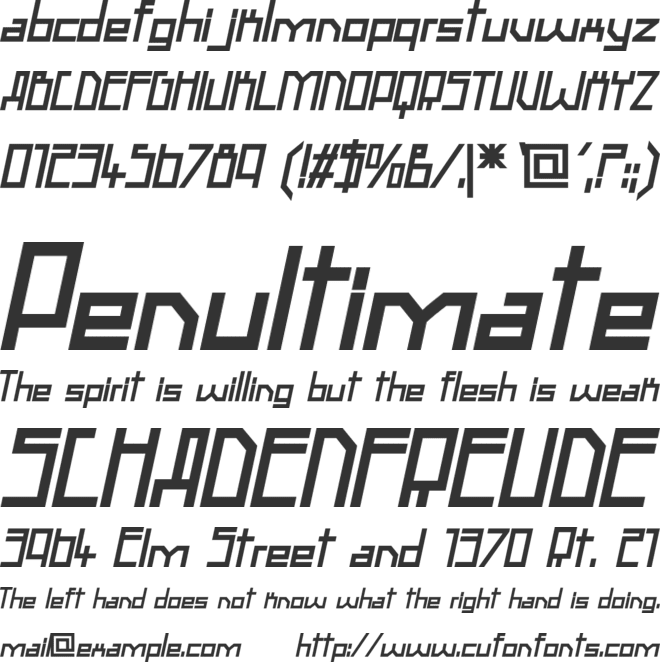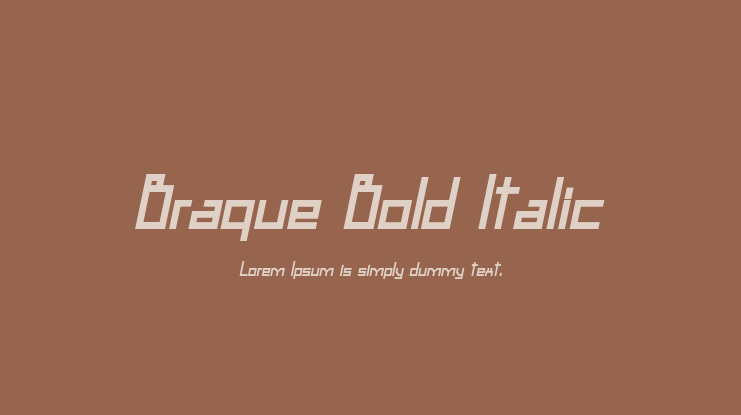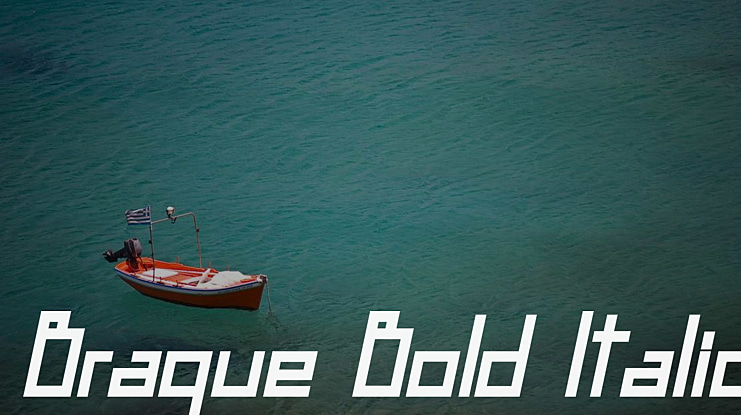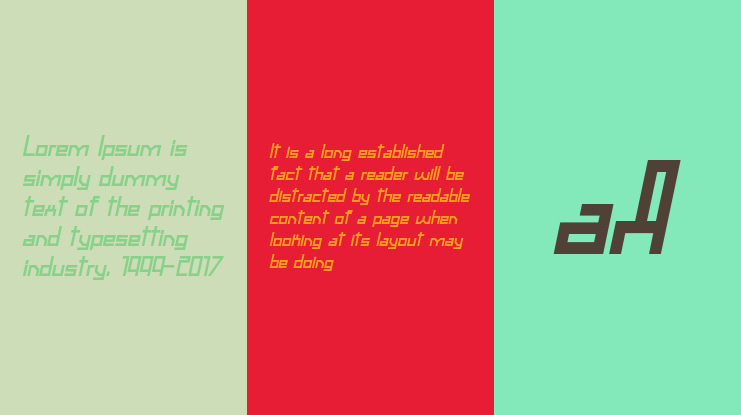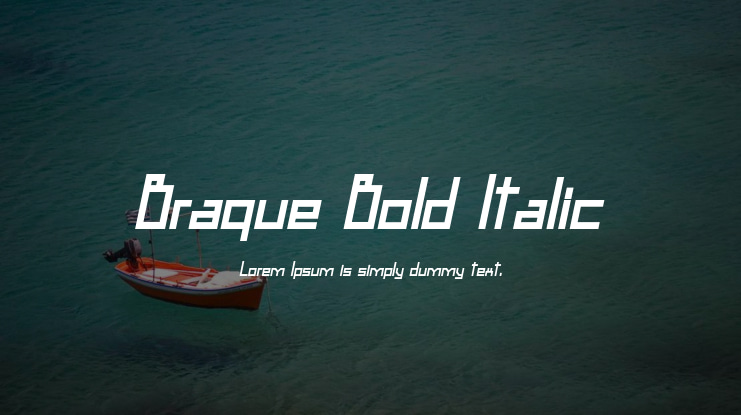
Braque Bold Italic Font Family
P.A.Vannucci
Dall’estro pittorico di Georges Braque, il font inedito che esprime l’estro artistico di una corrente figurativa che ha condizionato l’arte di ogni tempo. Un font disponibile in 12 formati True Type (Thin, UltraLight, Light, Book, Medium e Bold – Italic).